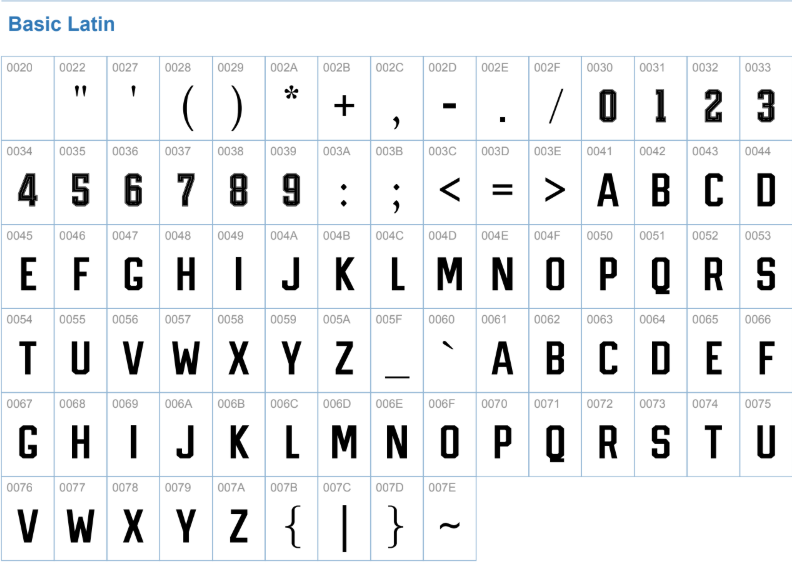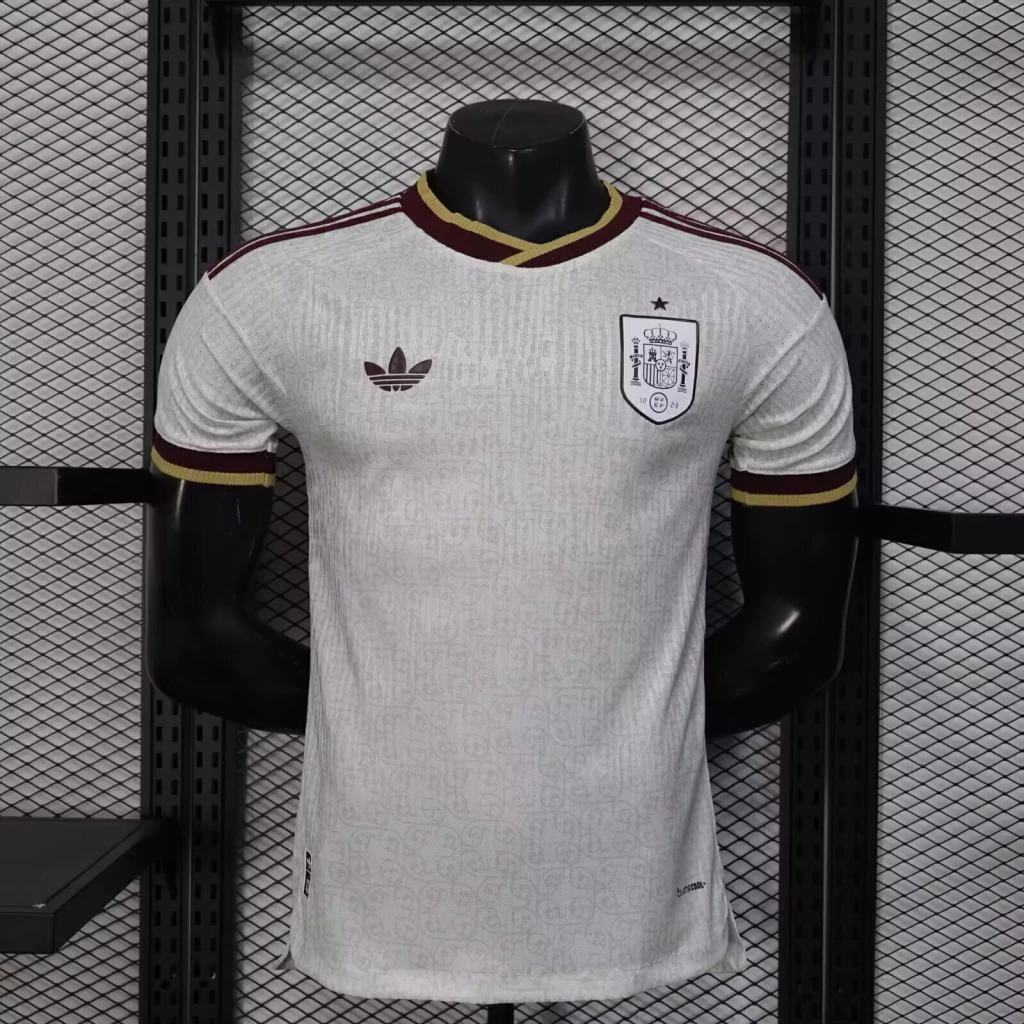
A nova temporada da Seleção Espanhola já está entre nós, e com ela chega um dos detalhes mais aguardados por designers e torcedores: a tipografia oficial do segundo uniforme de 2026. Mais do que um simples conjunto de letras, a fonte carrega a alma visual do time dentro de campo.
A identidade visual da Roja para este ciclo aposta em uma estética que une tradição e modernidade. O estilo dos números e nomes ganha ainda mais relevância com as transmissões em alta definição e a obsessão dos fãs por personalização de camisas. É aquele elemento que conecta o kit à torcida e aos projetos gráficos que pipocam nas redes sociais.
Estilo visual da tipografia
A fonte do segundo uniforme da Espanha 2026 apresenta números com traços dinâmicos e levemente alongados, transmitindo velocidade mesmo na leitura estática. Os acabamentos são limpos, sem serifas excessivas, o que garante ótima legibilidade tanto nos estádios quanto nas telas de TV e celular.
O desenho moderno conversa diretamente com os elementos gráficos do uniforme visitante, mas mantém uma sobriedade que respeita a história da seleção. É uma tipografia que respira futebol contemporâneo sem abrir mão da elegância.
Aplicação no uniforme
No uniforme titular, a Espanha tradicionalmente adota variações mais clássicas. Já no segundo uniforme de 2026, essa tipografia assume o protagonismo, com alto contraste sobre o tecido em tom claro característico do manto visitante. Caso o terceiro uniforme entre em campo, a mesma fonte costuma ser adaptada para manter a consistência visual da coleção.